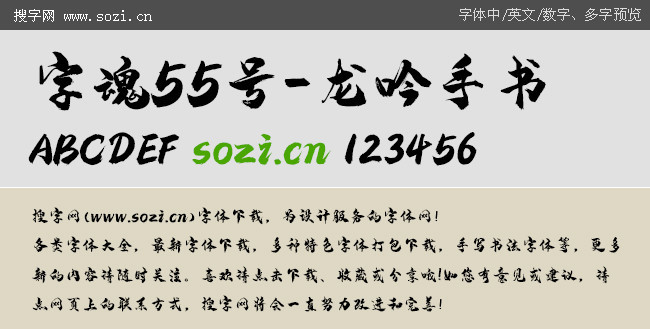
字魂55號(hào)-龍吟手書
搜字網(wǎng)提供一款字魂55號(hào)-龍吟手書中文字體下載,該字體是一款毛筆書法手寫字體,該字體包含9169個(gè)中文、字母、 符號(hào)和數(shù)字,具有中國風(fēng) 、有力、古典、穩(wěn)重、堅(jiān)硬 的風(fēng)格,可以滿足您設(shè)計(jì)上的各種需求,該字體主要用于標(biāo)志、導(dǎo)視、海報(bào)企宣、活動(dòng)展會(huì)、書籍 等場(chǎng)景。